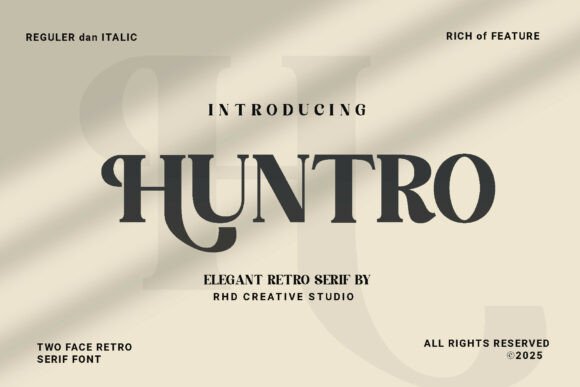
Huntro - Elegant Retro Serif
การค้นหาองค์ประกอบการออกแบบที่เหมาะสมอาจเป็นเรื่องท้าทาย แต่ Huntro - Elegant Retro Serif นำเสนอคอลเลกชันที่โดดเด่นซึ่งช่วยยกระดับงานของคุณได้ทันที
สร้างขึ้นอย่างแม่นยำ Huntro - Elegant Retro Serif ให้เวกเตอร์ที่สะอาด พิมพ์ตัวอักษรที่ราบรื่น และใบอนุญาตเชิงพาณิชย์เพื่อความสบายใจ
ไม่ว่าคุณจะสร้างผลิตภัณฑ์ POD (Print on Demand) คำเชิญงานแต่งงาน หรือกราฟิกโซเชียลมีเดีย Huntro - Elegant Retro Serif ก็เหมาะสมอย่างยิ่ง